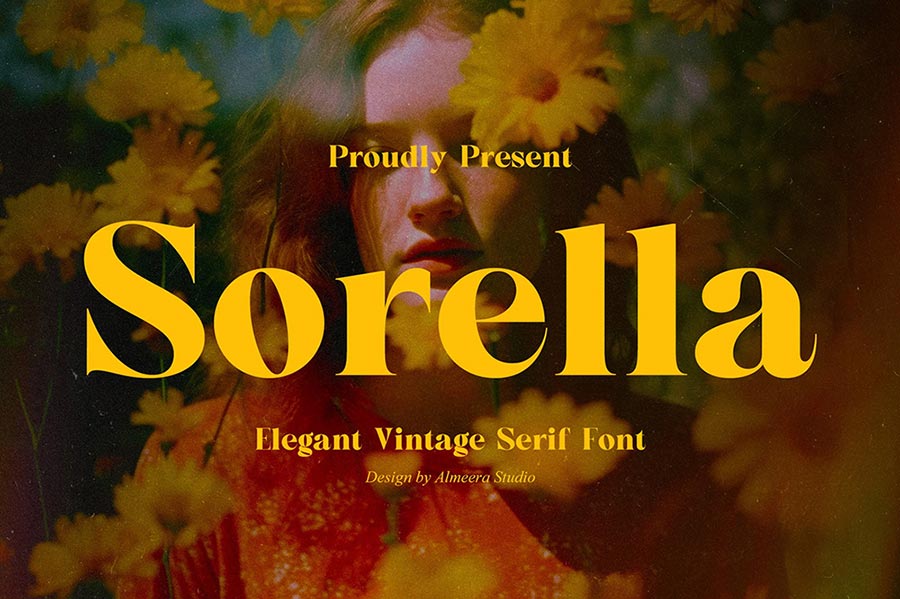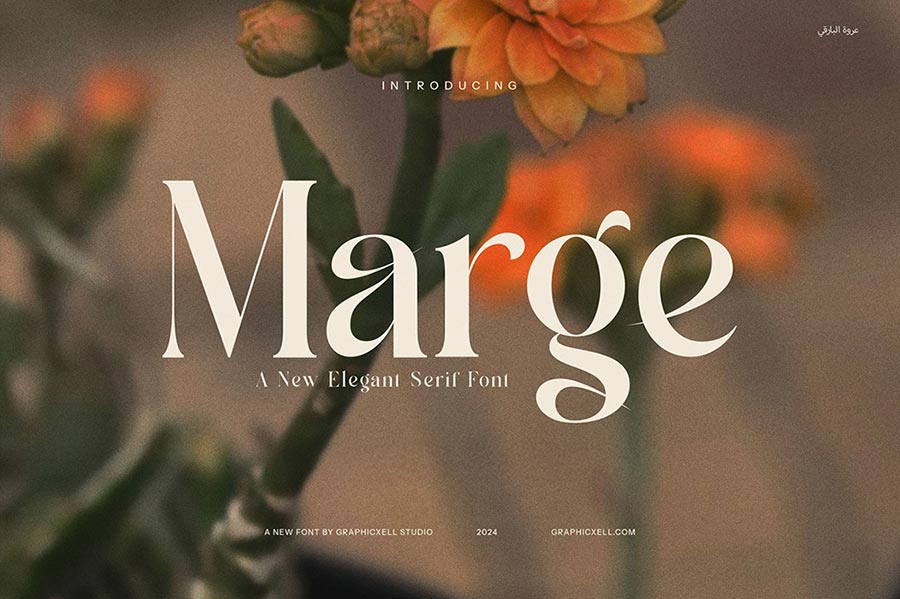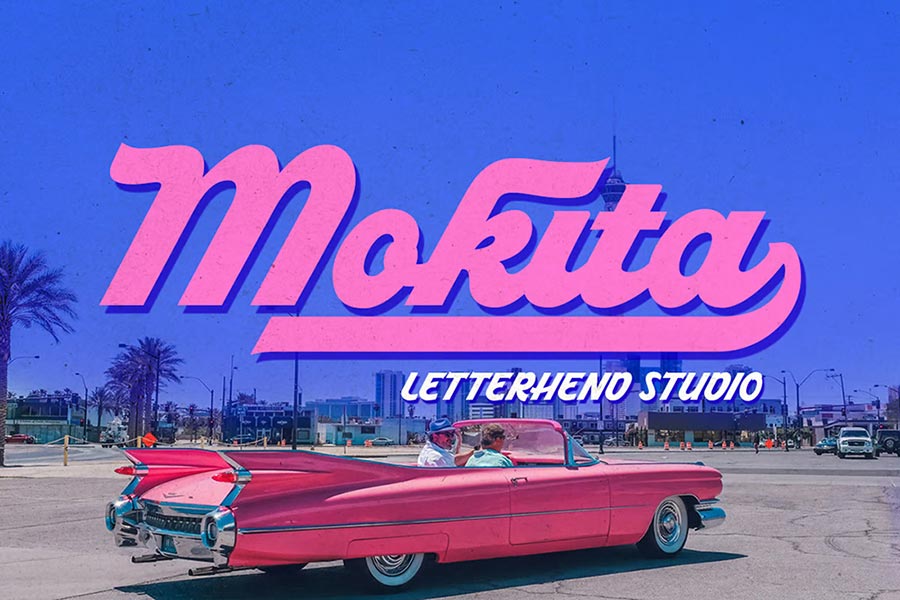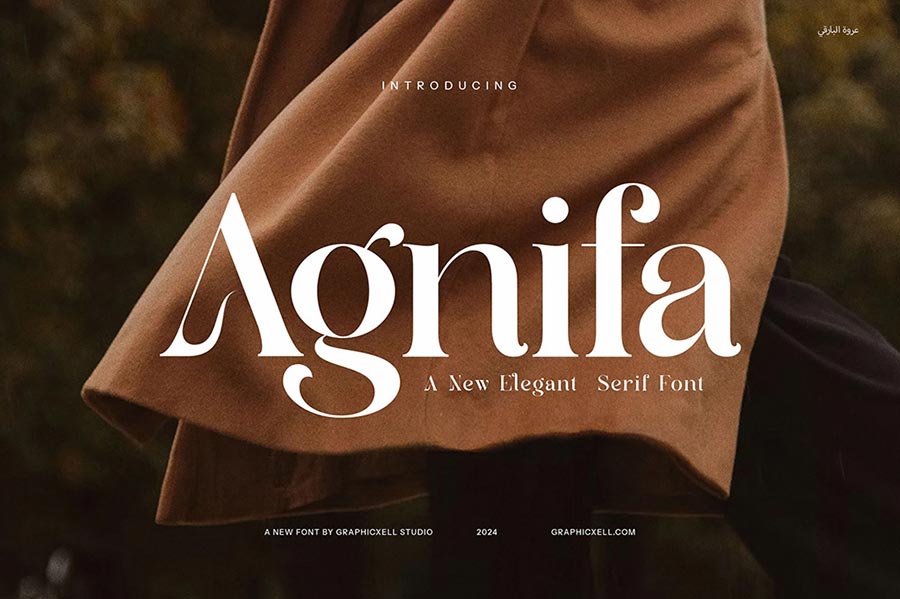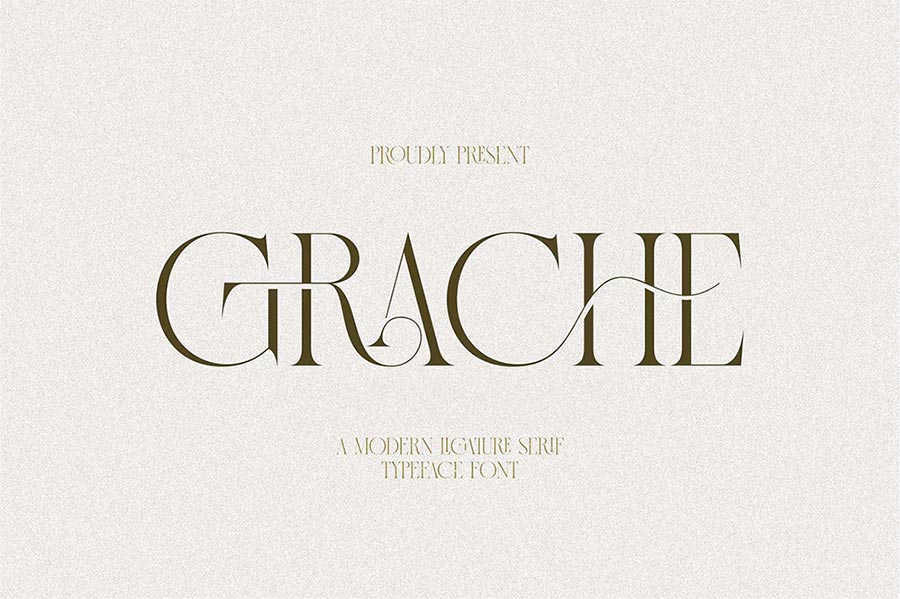
Trong ngành thiết kế đồ họa, việc cập nhật và sử dụng những font chữ mới không chỉ mang lại sự tươi mới cho các dự án mà còn giúp tăng tính sáng tạo và chuyên nghiệp. Hiểu được nhu cầu này, sadesign.vn đã chia sẻ miễn phí 5+ font chữ siêu độc đáo dành cho năm 2025. Đây là cơ hội tuyệt vời để các nhà thiết kế nâng cấp bộ sưu tập font của mình mà không phải tốn bất kỳ chi phí nào.
Tại Sao Font Chữ Quan Trọng Trong Thiết Kế?
Font chữ không chỉ là công cụ truyền tải thông điệp mà còn là yếu tố quyết định đến cảm xúc và sự chú ý của người xem. Một font chữ phù hợp có thể làm nổi bật thương hiệu, tạo sự khác biệt và truyền tải đúng tinh thần của dự án. Vì vậy, việc lựa chọn những font chữ mới mẻ, hiện đại là điều cần thiết để bắt kịp xu hướng thiết kế trong thời đại số.
Điểm Nổi Bật Của Bộ Font Chữ Năm 2025
Bộ font chữ mà sadesign.vn chia sẻ được thiết kế với tiêu chí sáng tạo, hiện đại và đa năng. Dưới đây là một số đặc điểm nổi bật:
1. Phong Cách Đa Dạng: Bao gồm các kiểu chữ từ tối giản, thanh lịch đến phức tạp, nghệ thuật, phù hợp với nhiều loại dự án khác nhau.
2. Tối Ưu Hóa Hiển Thị: Các font được thiết kế để hiển thị hoàn hảo trên cả màn hình kỹ thuật số lẫn in ấn.
3. Hỗ Trợ Đa Ngôn Ngữ: Phù hợp với nhiều ngôn ngữ, giúp các nhà thiết kế dễ dàng sử dụng trong các dự án quốc tế.
Những Font Chữ Được Yêu Thích Trong Bộ Sưu Tập
Dưới đây là một số font chữ tiêu biểu trong bộ sưu tập:
- Font 1: Phong cách hiện đại, tối giản, phù hợp với các dự án thương hiệu.
- Font 2: Mang hơi hướng cổ điển pha lẫn hiện đại, tạo điểm nhấn độc đáo.
- Font 3: Thiết kế mềm mại, lý tưởng cho các dự án về thời trang hoặc mỹ thuật.
- Font 4: Kiểu chữ mạnh mẽ, góc cạnh, phù hợp với các thiết kế công nghệ hoặc game.
- Font 5: Phong cách viết tay tự nhiên, tạo cảm giác gần gũi và thân thiện.
Kết Luận